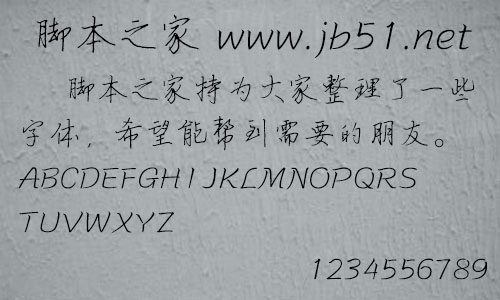
小美體字體是一款中文藝術(shù)字體,這款字體筆觸較為纖細(xì),字體清晰明朗,筆畫流暢灑脫,整體有種不羈的感覺(jué),適合應(yīng)用于藝術(shù)設(shè)計(jì)、平面宣傳設(shè)計(jì)、網(wǎng)頁(yè)設(shè)計(jì)、書法字帖等領(lǐng)域,需要的朋友可以前來(lái)本站下載。